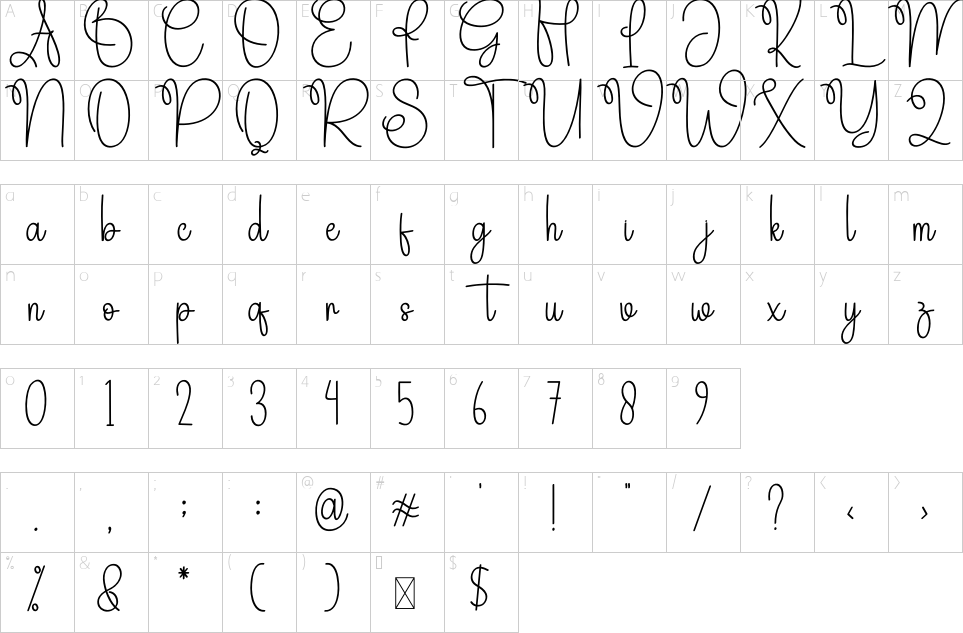
Descubra a beleza da Samantha Signature font com essa elegante e sofisticada fonte. Projetada pelo designer desconhecido, Samantha Signature é uma opção perfeita para designers e criadores de conteúdo em busca de um estilo sofisticado e elegante. Seu design elegante torna-a perfeita para utilizar em nomes de marca, materiais de design impresso e até em projetos digitais de e-mail marketing. Com um download de 1.176 vezes, Samantha Signature se tornou uma fonte popular e amada. Descubra por si mesmo o encanto desta fonte única e elegante. Download Samantha Signature font para Windows e Mac e encontre a sua perfeição.